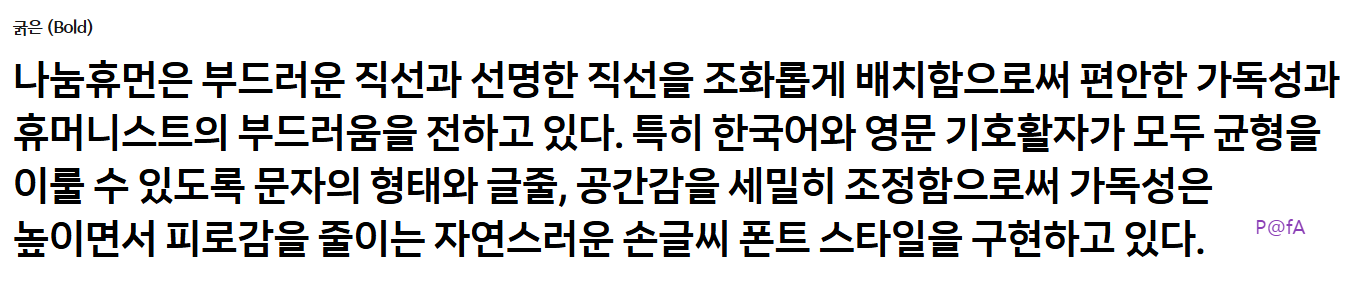
네이버에서 무료로 제공하는 나눔 글꼴 중의 하나인 나눔휴먼은 선명한 직선이 특징인 고딕체에 부드러운 곡선을 추가한 자연스러운 손글씨 스타일로 제작한 글꼴로, 한글 2480자를 비롯해서 라틴 191자 그리고 약물 986자로 구성되어 있다. 특히 폰트 굵기에 따라 6종의 글꼴을 제공하므로 제목뿐만 아니라 본문에도 사용할 수 있을 정도로 활용 범위가 넓다. 다음에서 제시하는 순서대로 따라하면 나눔휴먼을 무료로 다운로드해서 사용할 수 있다.
네이버 나눔휴먼은 손글씨의 부드러움을 담은 고딕체 계열의 글꼴로, 일상적으로 사용할 수 있는 자연스러운 스타일을 구현하고 있다. 즉, 직선적인 고딕체에 손글씨로 부드러운 곡선 처리를 추가한 휴머니스트 폰트로 형상화하며 따듯함이 전해지는 글꼴이다.
나눔휴먼은 부드러운 직선과 선명한 직선을 조화롭게 배치함으로써 편안한 가독성과 휴머니스트의 부드러움을 전하고 있다. 특히 한국어와 영문 기호활자가 모두 균형을 이룰 수 있도록 문자의 형태와 글줄, 공간감을 세밀히 조정함으로써 가독성은 높이면서 피로감을 줄이는 자연스러운 손글씨 폰트 스타일을 구현하고 있다.
해당 나눔휴먼 글꼴을 담은 NanumHuman 폴더에서 보기 옵션을 아주 큰 아이콘으로 설정하면 글꼴 형태를 대략적으로나 가늠할 수 있다. 즉, 전체적으로 직선의 간결함에 곡선의 부드러움이 추가되어 자연스러운 폰트에서도 가독성을 확보하면서 피로감은 상대적으로 줄이는 효과를 발휘한다. 다음에서 나눔휴먼 폰트를 윈도우용 PC에 설치하는 과정을 중심으로 살펴본다.